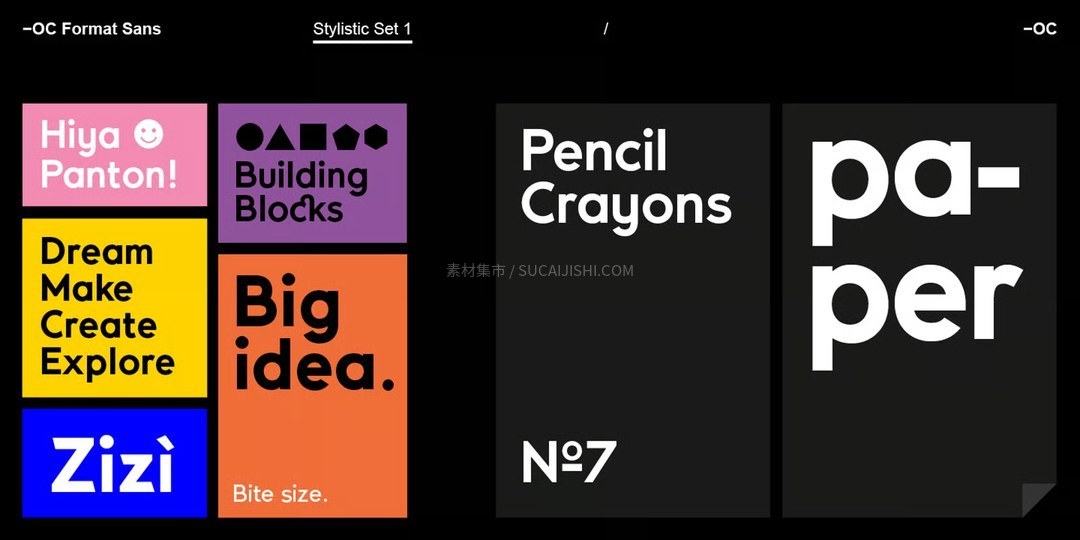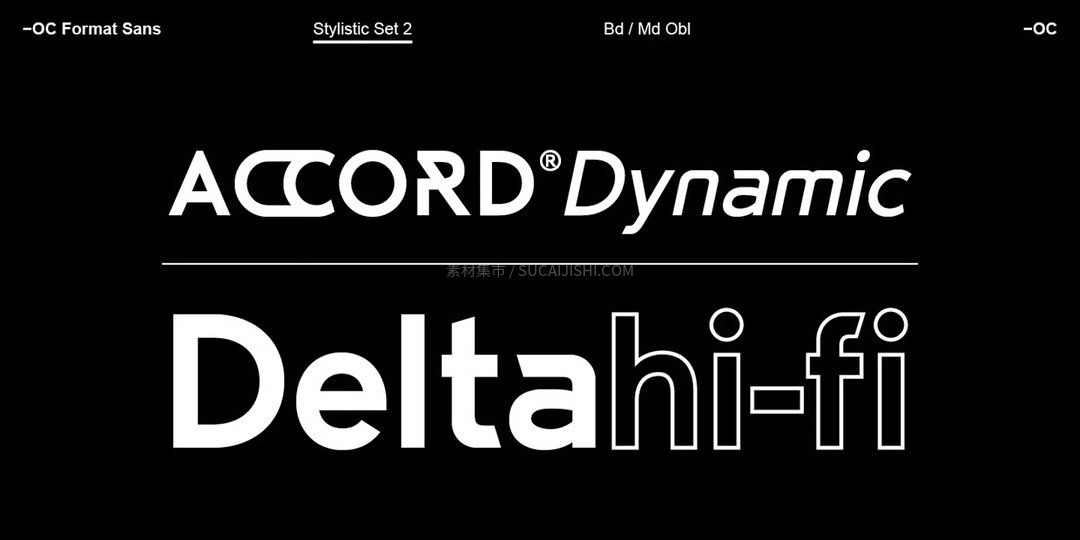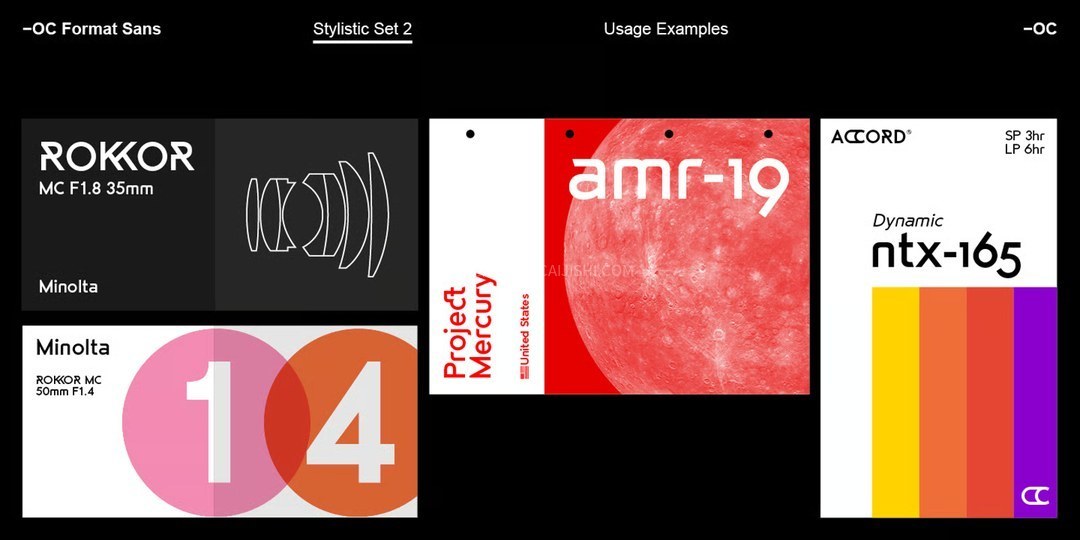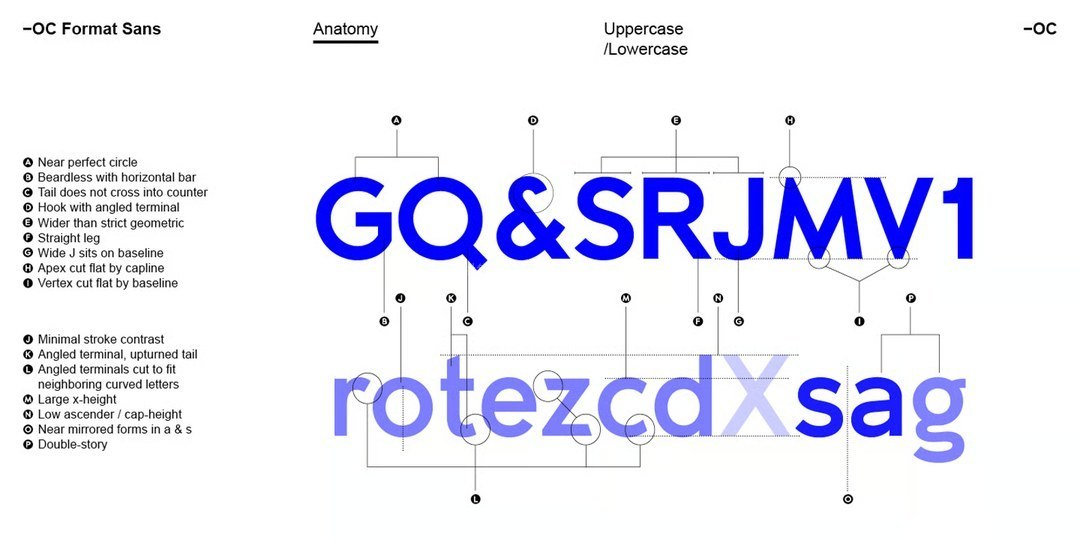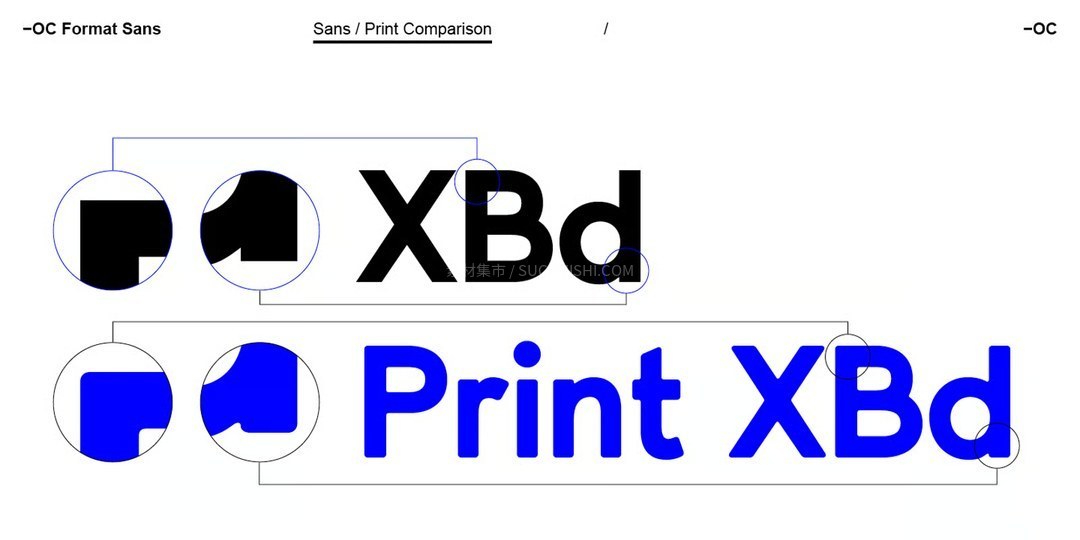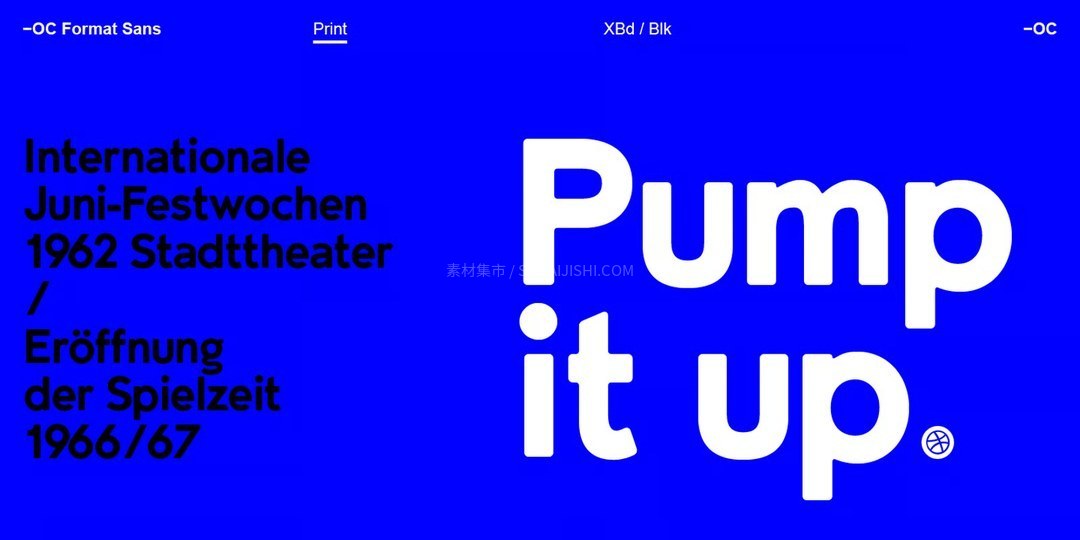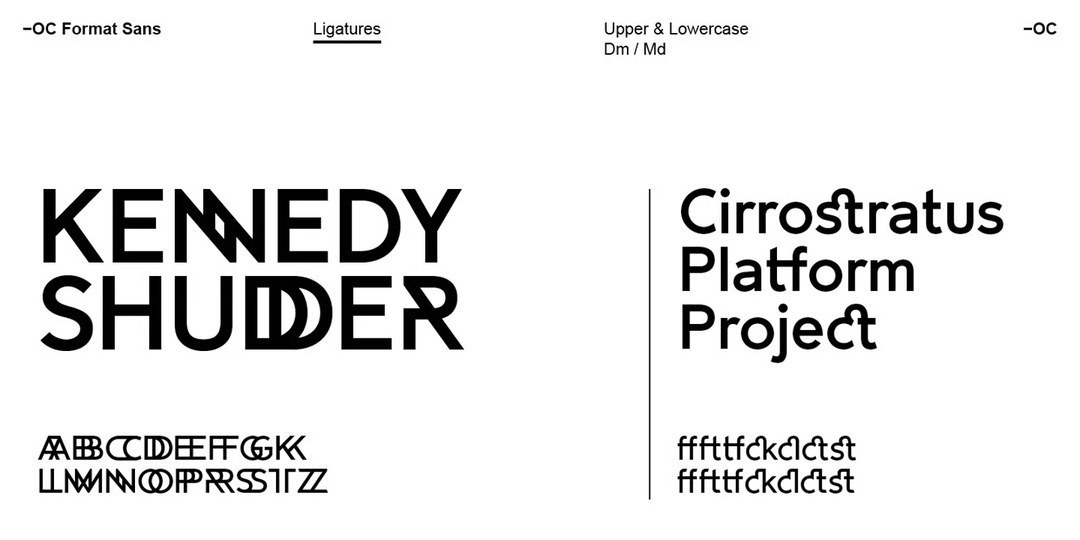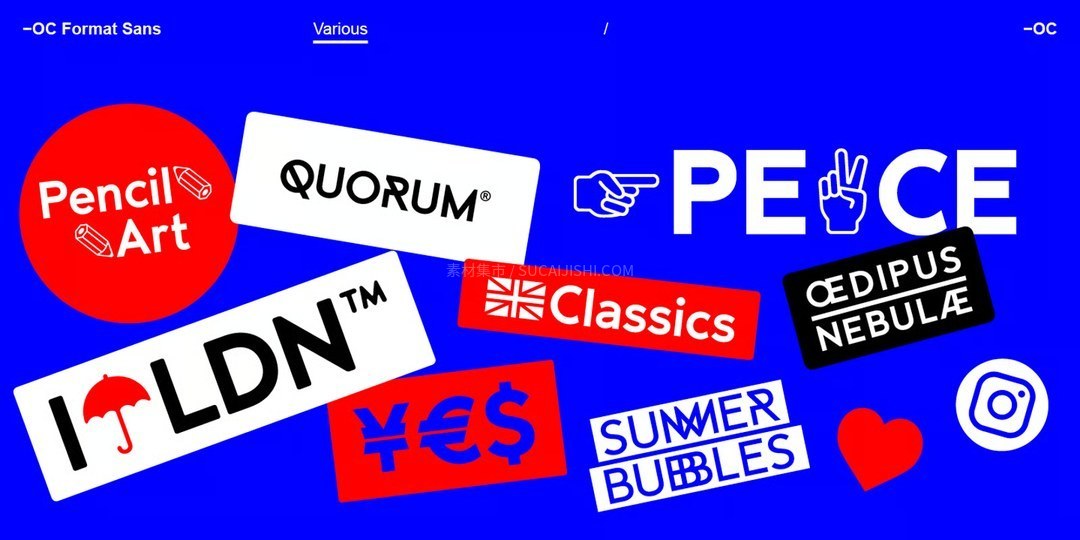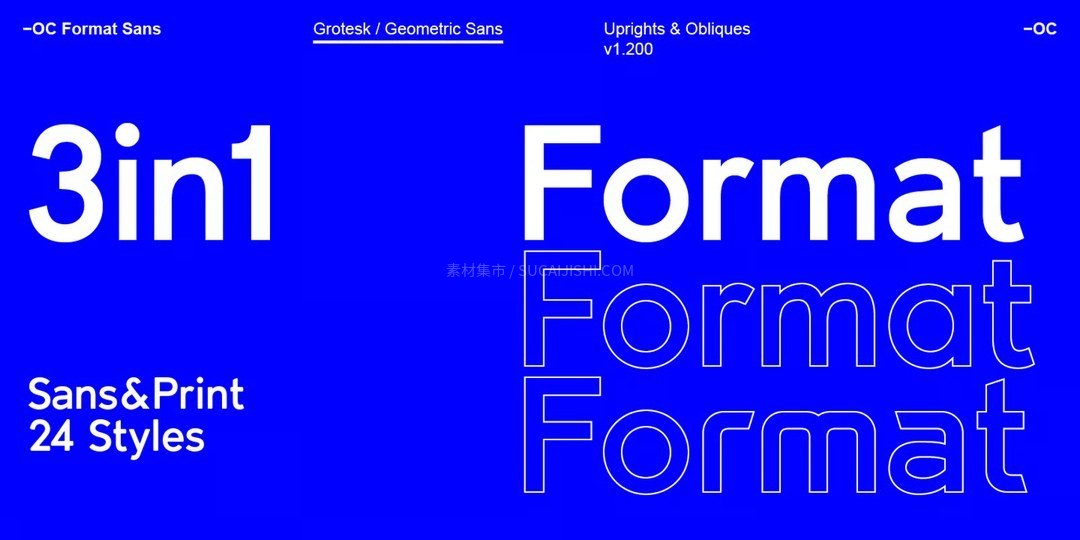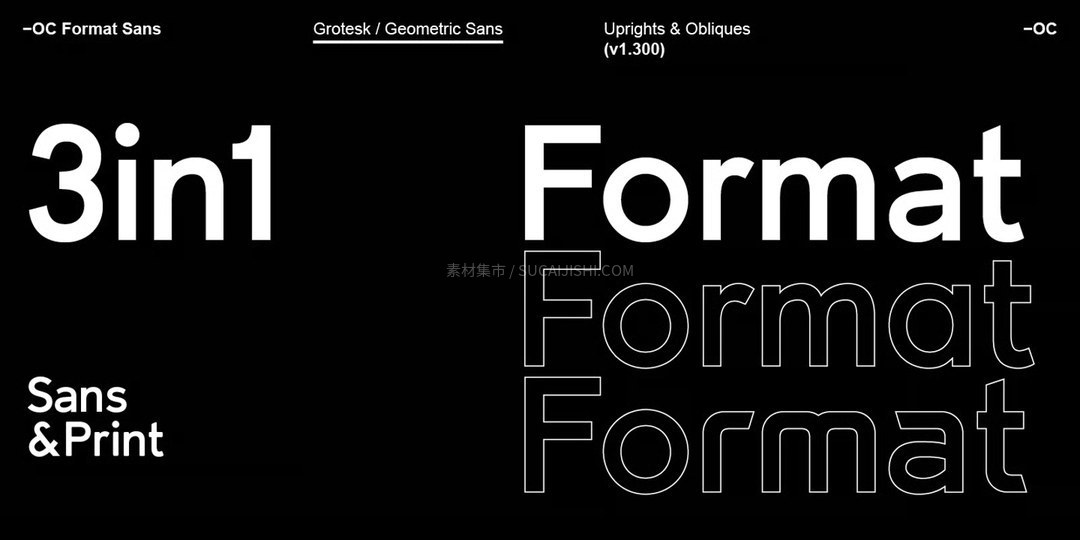
OC Format Sans几何无衬线字体家族
家人们,今天给大家分享一款超级宝藏的几何无衬线字体——OC Format Sans v1.3!这款字体已经是第三代升级版啦,完美融合了经典 Futura 的风格和 Akzidenz 的韵律比例,简直是排版界的天花板! 全套包含 24 款精美样式,最绝的是它分为“标准版”和全新的“Print 印刷版”。Print 版本特意柔化了边缘,完美模拟了油墨在非涂布纸上晕染的复古质感,瞬间给数字媒体作品注入满满的温润亲切感! 它的设计细节超级用心,笔画粗细均匀,默认的双层 a 和 g 带着浓浓的学术气息;如果切换到 Set 1 样式瞬间变得友好可爱,Set 2 样式则科技感拉满!这款字体不仅字距打磨得极其精细,还自带超级丰富的 OpenType 功能(包括标准连字、社交图标、符号和罗马数字等)。无论你是做高级质感的品牌Logo设计,还是超长篇的杂志排版,它都能轻松Hold住!设计师小伙伴们赶紧马住,绝对是你字库里超实用的一款排版利器!